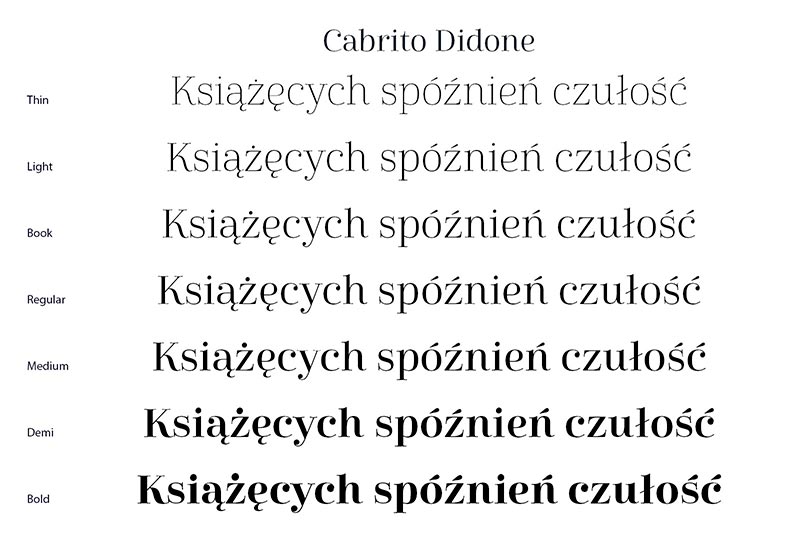
Font Cabrito Didone
Cabrito Didone to kolejny font projektu Jeremiego Dooleya w naszym studiu. Rodzina składa się z 42 odmian i ma polskie ogonki. To elegancki font szeryfowy zalecany zwłaszcza do projektów czasopism.